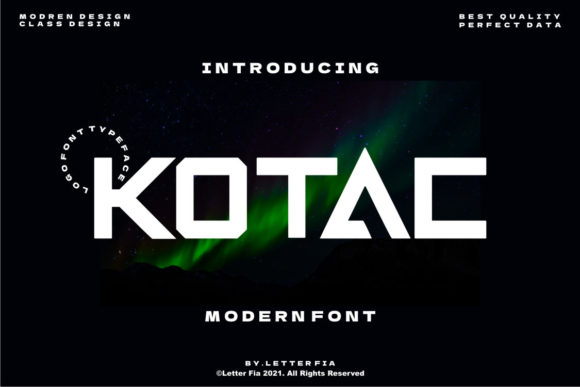
Creativefabrica Kotac Font
[Creativefabrica] Kotac Font
Kotac - это крутой, смелый и роботизированный шрифт.
Независимо от темы, этот шрифт будет невероятно полезен в вашей библиотеке шрифтов, поскольку он способен приподнять любое творение.